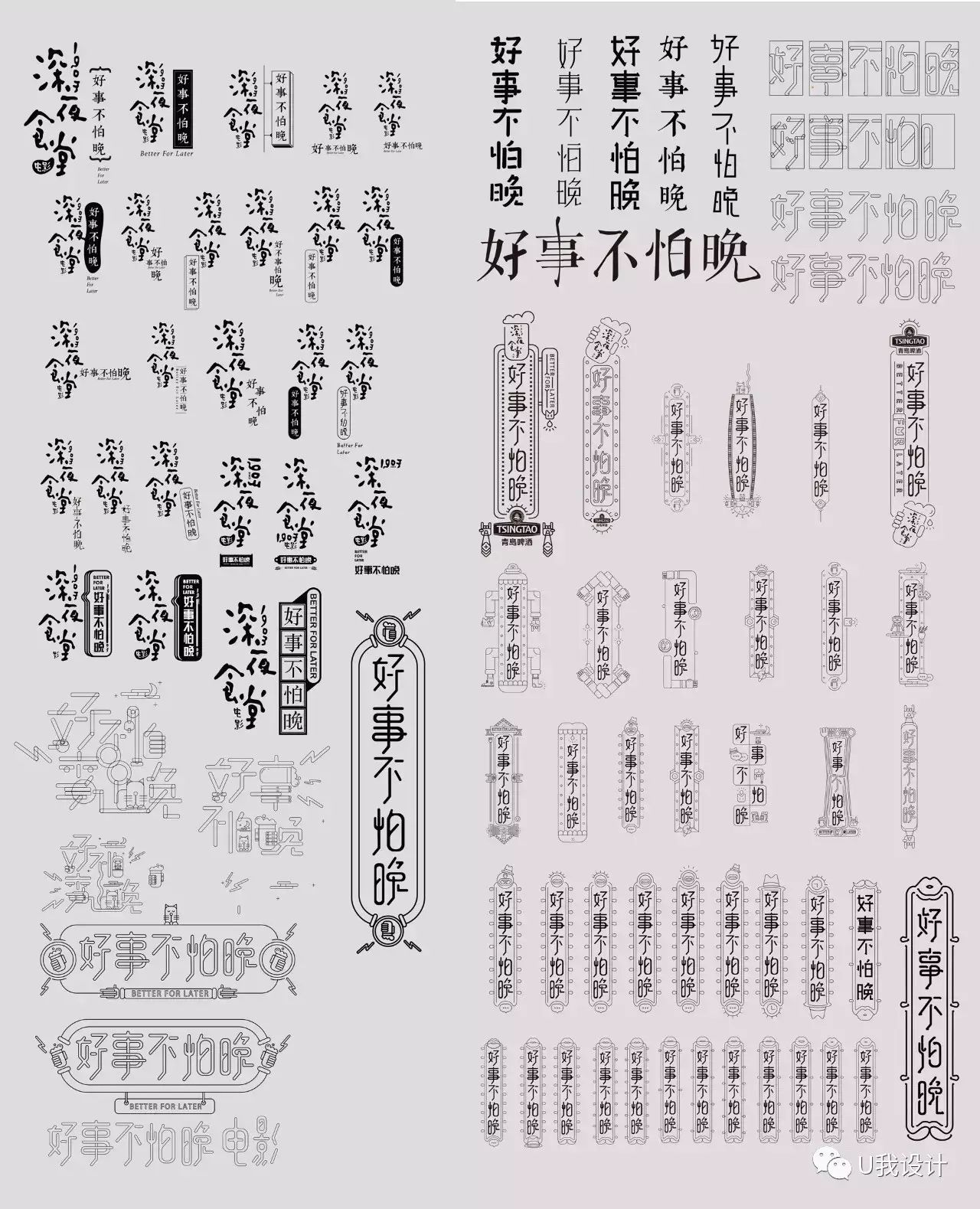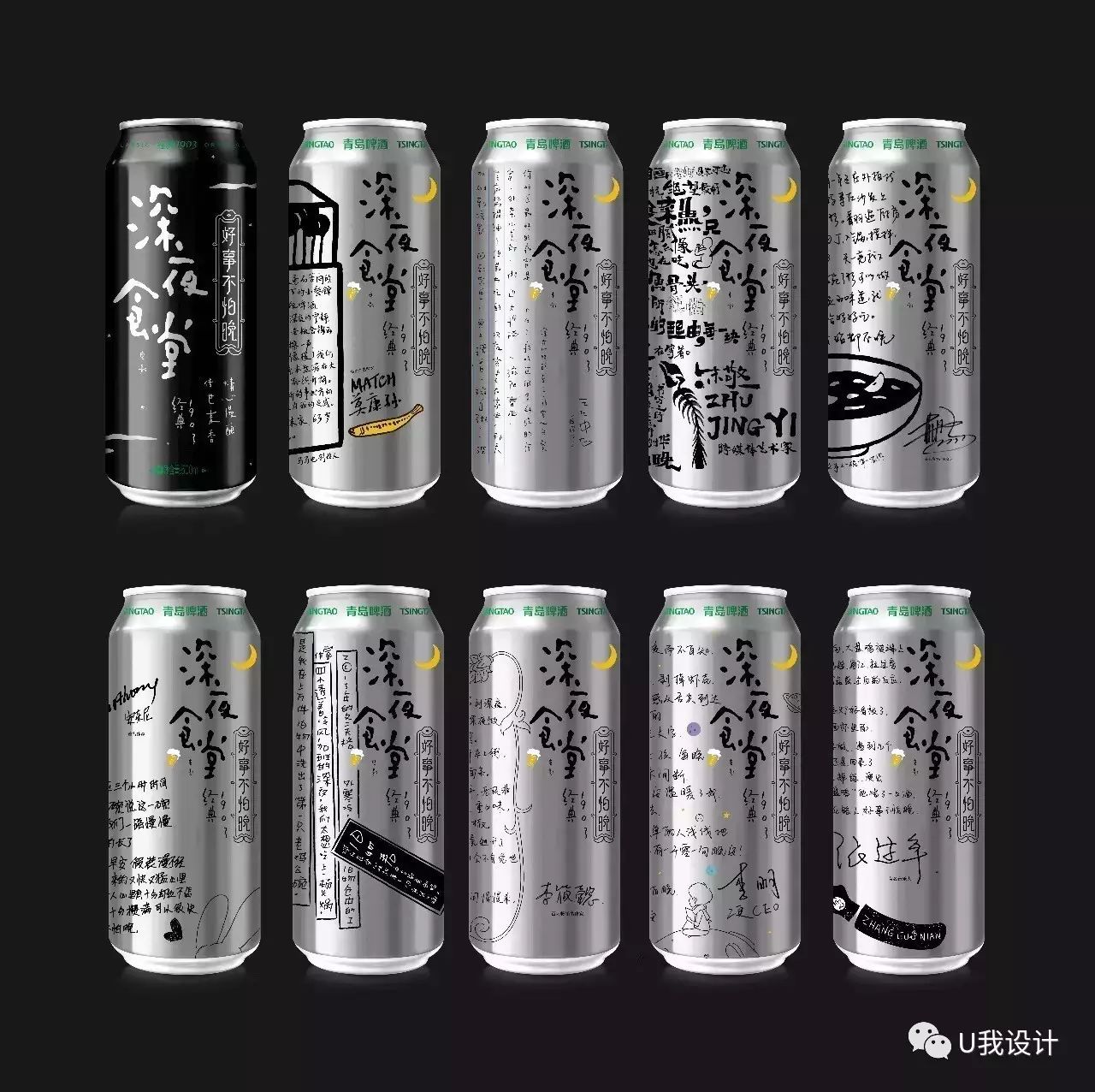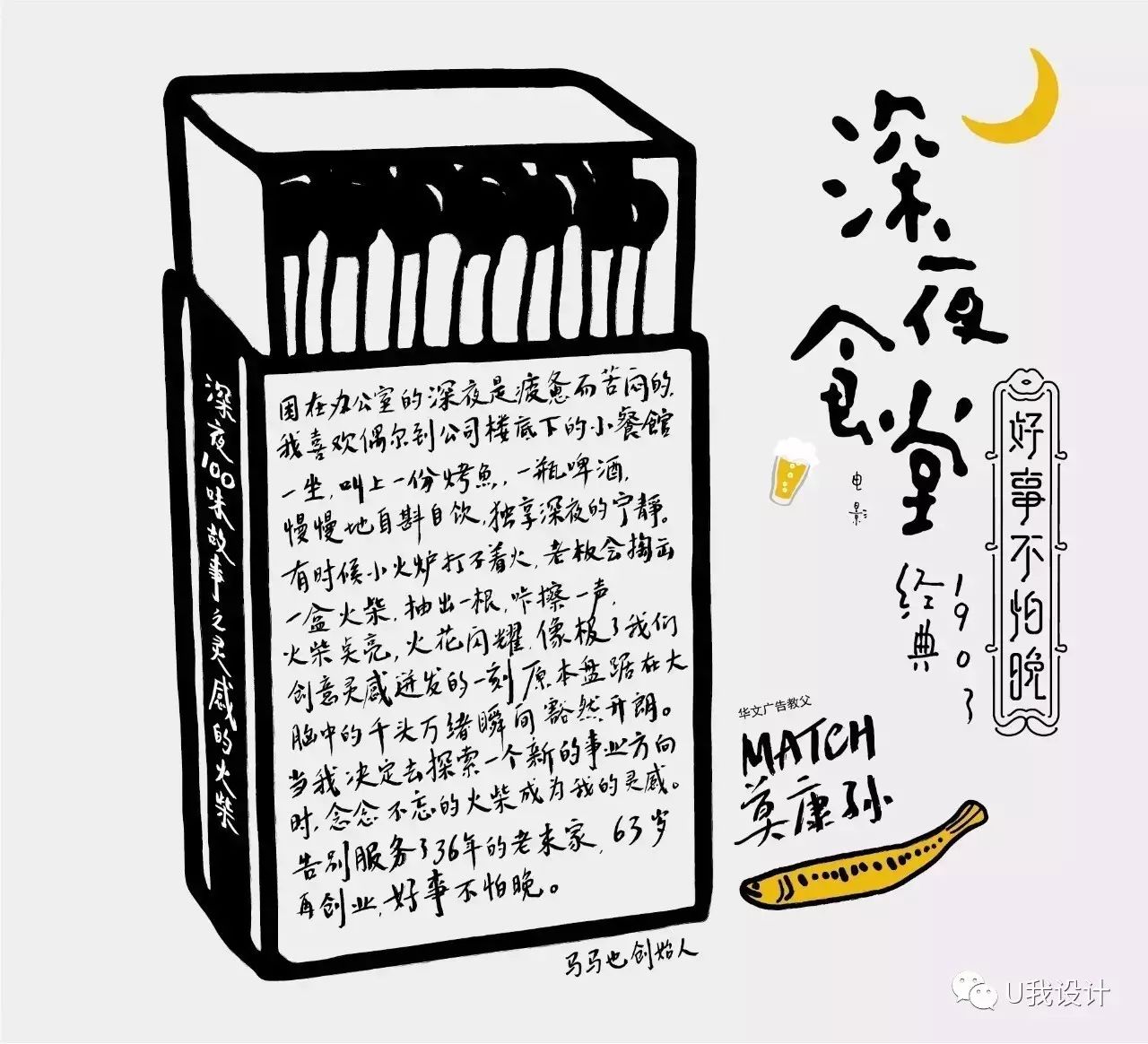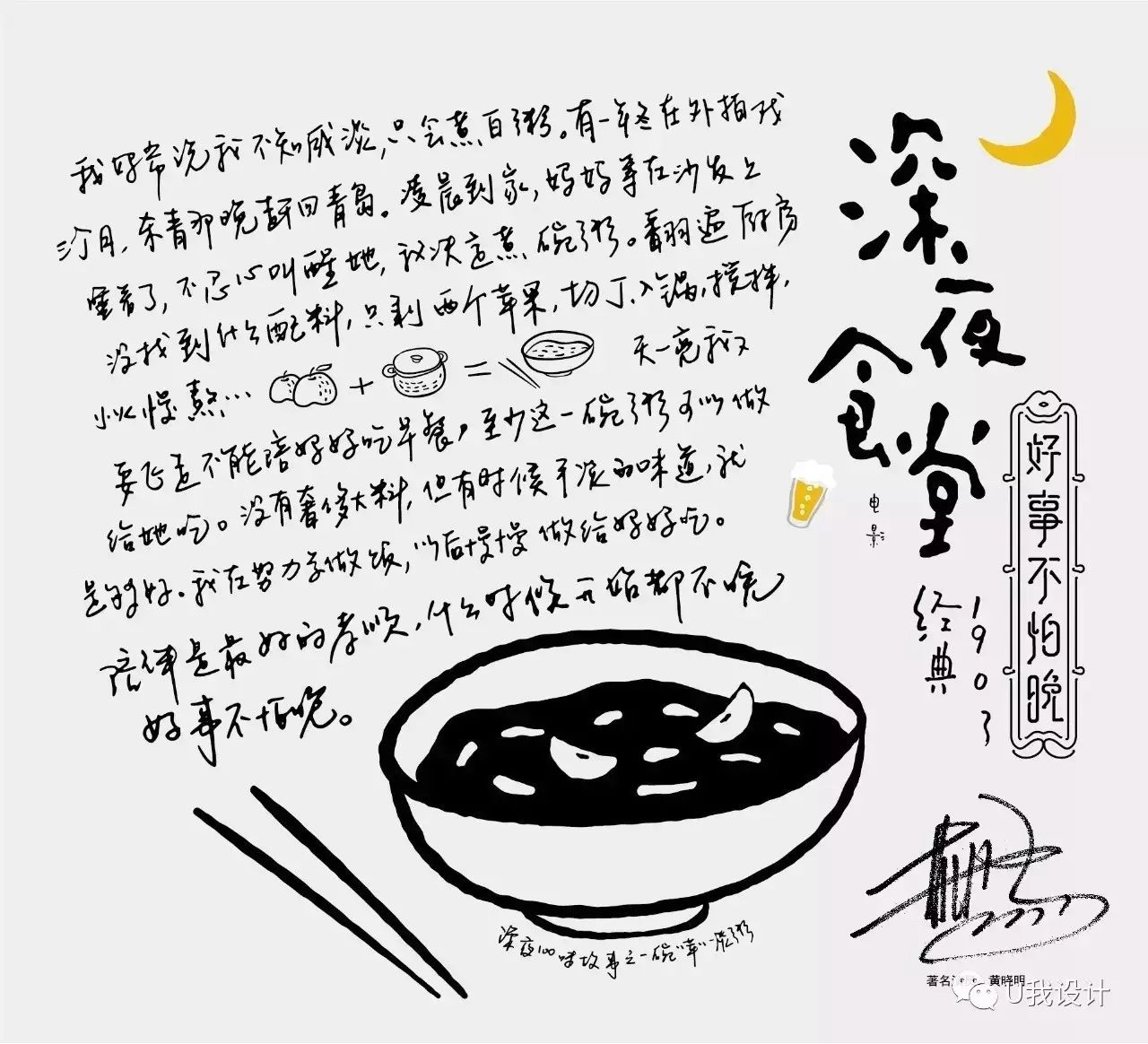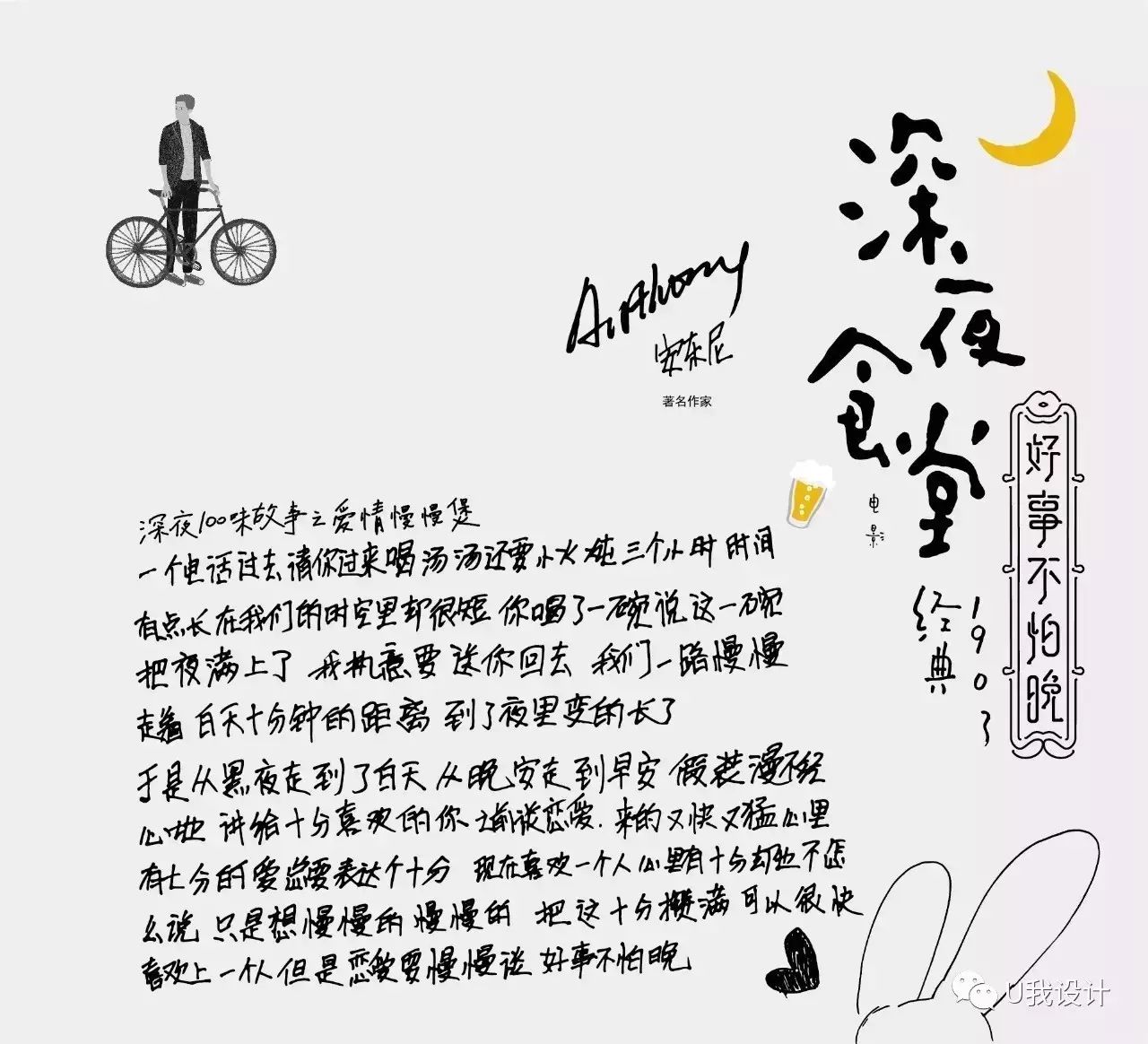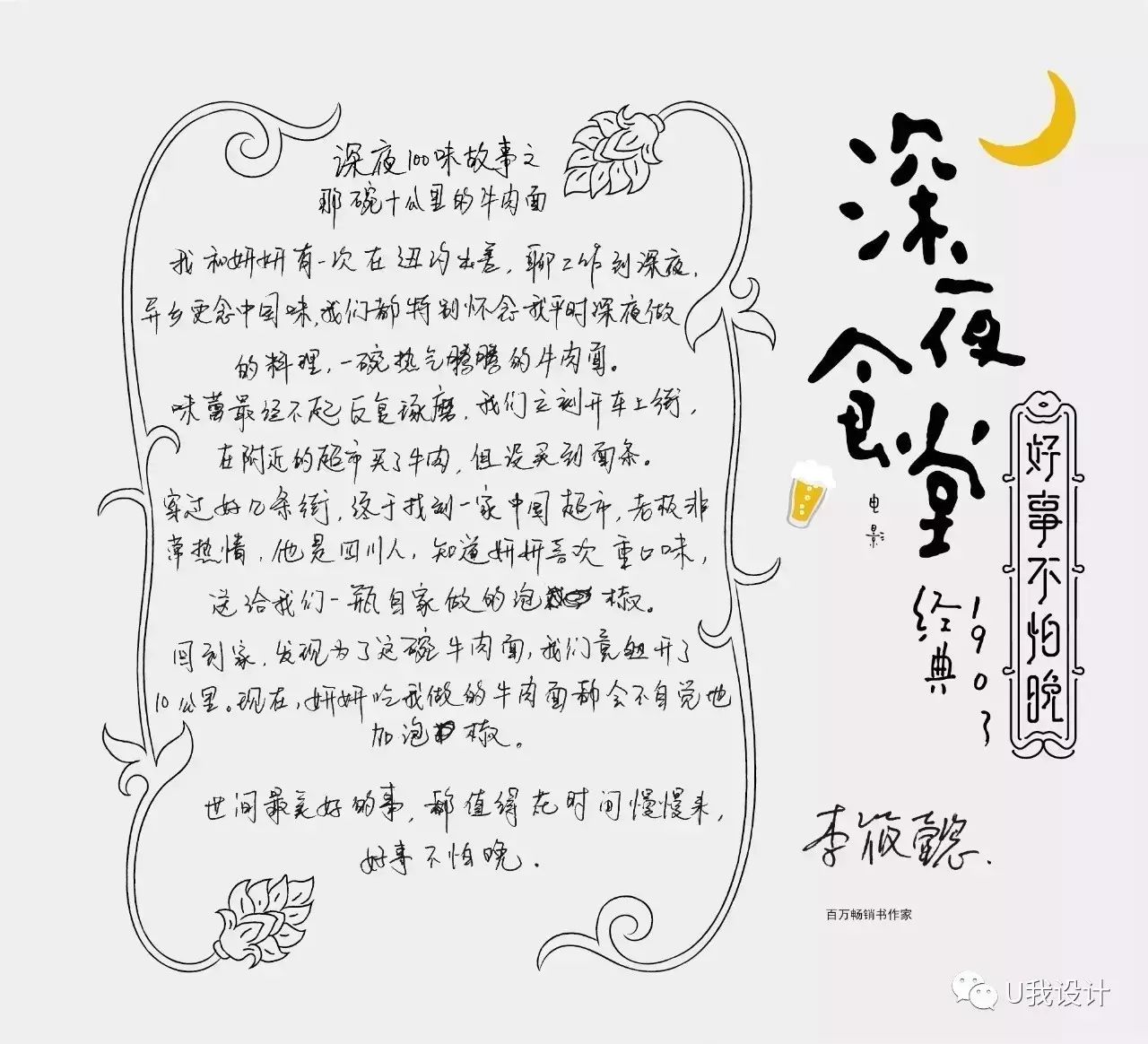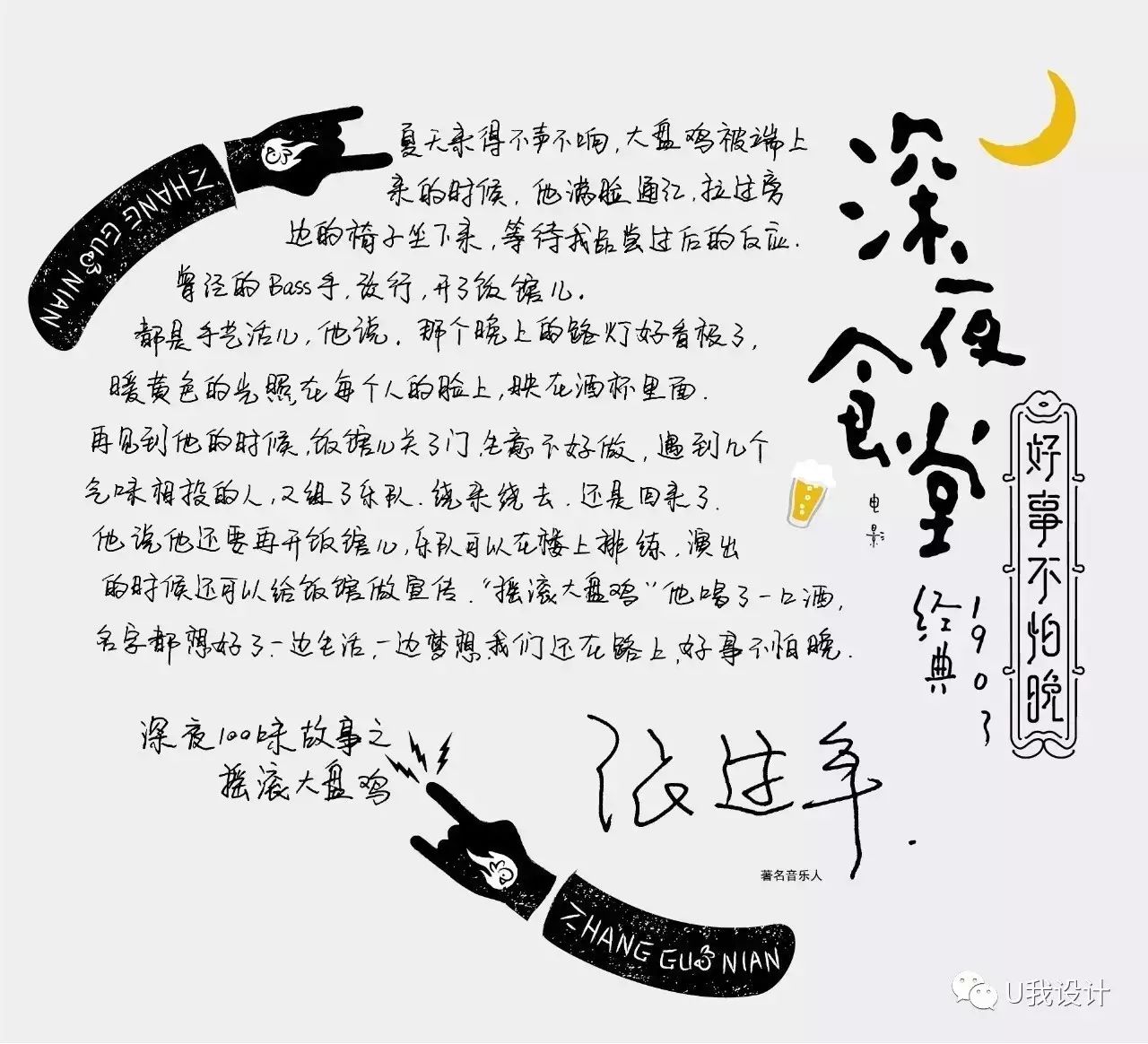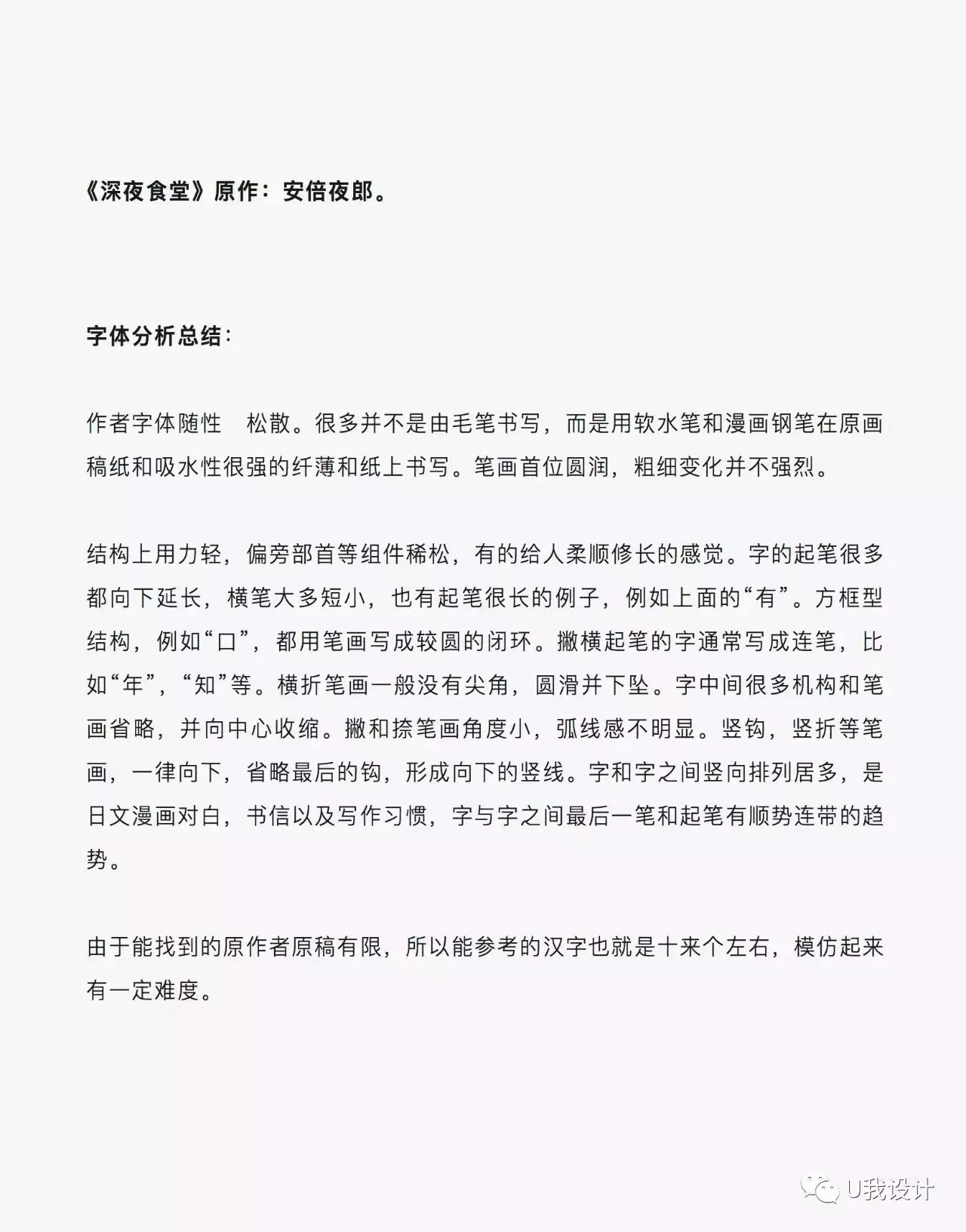
青岛啤酒字体设计案例
前言:最近,天与空为青岛啤酒打造的#中国人的深夜食堂#火遍网络,从”长城上的深夜食堂”艺术事件,到广受好评的“深夜罐”,再到KOL系列故事罐,这一系列的“设计”都非常亮眼,这些设计的背后有怎样的故事呢?
先从这个大胆全黑的“深夜罐”说起,
且听天与空负责本次传播的幕后“黑手”:
天与空创意合伙人黄海波怎么说,
“之所以选择黑色,
是因为我们做的是“深夜食堂”,
黑是深夜的颜色,
青岛啤酒诞生114年以来,
从来没有出过纯黑色的包装,
这是第一次。”
“上面这个月亮,
安倍夜郎日本版《深夜食堂》漫画中就有,
一直沿用,我们这次把它放大,
然后搬到了长城上。”
“月亮在中国的文化里,
不只是夜晚的象征,
还有更多的诗意,
它和长城组合,
不只是好看,
还有更强烈的意义。”
网友说的罐子,就是6月19日
青岛啤酒包下中国最长的长城:
慕田峪长城发布的
与电影“深夜食堂”合作的限量版“深夜罐”。
这是百年青啤,
首次推出的一款适合深夜享用的啤酒,
从经典的绿罐到“深夜”的黑罐,
等了114年,可谓好事不怕晚,
深夜罐一上市就大受欢迎,
销量不断上升。
这款深夜罐的设计,
遵循了原漫画“深夜食堂”的美学风格,
比如字体:
发生在深夜食堂的故事,
用霓虹灯效果当然更合适。
“好事不怕晚,这句SLOGAN有多重含义,第一层含义是好饭不怕晚,是深夜食堂的本义;第二层含义是好的啤酒要花时间慢慢酿,源自青岛经典1903,精心慢酿;第三层含义是人生不要急,抓住现在,好事自然来。”据说光设计这个就不下20多个版本,应了哪句,好事不怕晚。
6月19日晚,在慕田峪长城烽火台上除了推出“深夜罐”,还发布了9个“故事罐”。
邀请明星黄晓明、作家安东尼、自媒体人王左中右作家李筱懿、跨媒体艺术家朱敬一、华文广告教父莫康孙、音乐人张过年、二更食堂李明、旧物君等9位联合推出个人定制装——故事罐。罐身上是他们手书的深夜故事,每个故事都在讲述同一个主题:#好事不怕晚#。
“手写的字体,
好像在写一封信,
无论是不是明星,
故事是平等的。”
跨媒体艺术家朱敬一X深夜食堂X青岛啤酒经典1903
华文广告教父莫康孙X深夜食堂X青岛啤酒经典1903
明星黄晓明X深夜食堂X青岛啤酒经典1903
最爱深圳的人旧物君X深夜食堂X青岛啤酒经典1903
作家安东尼X深夜食堂X青岛啤酒经典1903
二更ceo 李明X深夜食堂X青岛啤酒经典1903
百万畅销书作家李筱懿X深夜食堂X青岛啤酒经典1903
自媒体王左中右X深夜食堂X青岛啤酒经典1903
音乐人张过年X深夜食堂X青岛啤酒经典1903
这一天晚上,
跨媒体艺术家朱敬一,歌手张过年来到现场,
和综艺达人及一些年轻人围坐在烽火台上,
烤腰子,羊肉串,啤酒,花生加毛豆…
弹琴、唱歌、喝酒、玩直播,
分享各自的深夜美食故事。
最触动人心的,
永远不是特别制作,
而是在我们身上发生的故事。
网友故事图
经典1903深夜罐和故事罐,
就是这么一款“慢性子的啤酒” ,
适合在深夜以美食和故事佐酒的我们。
故事罐将陆续上市,
好事不怕晚。